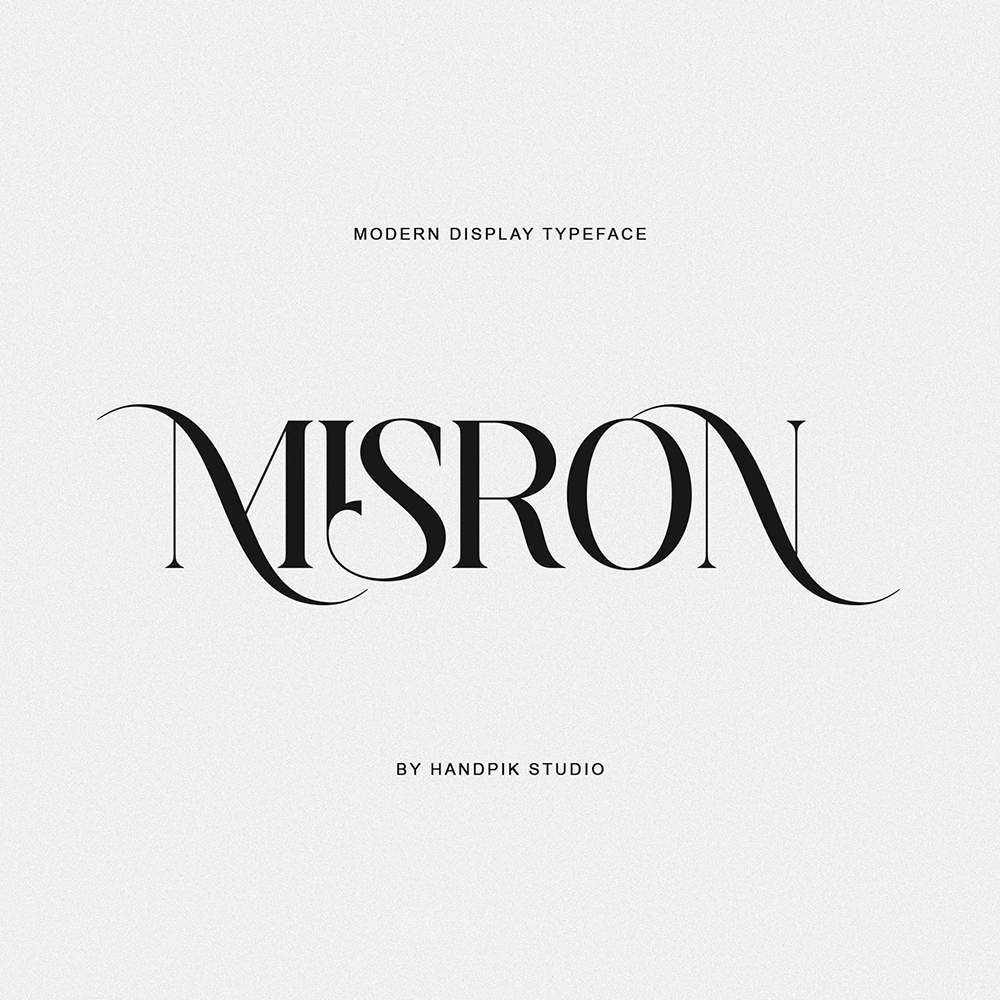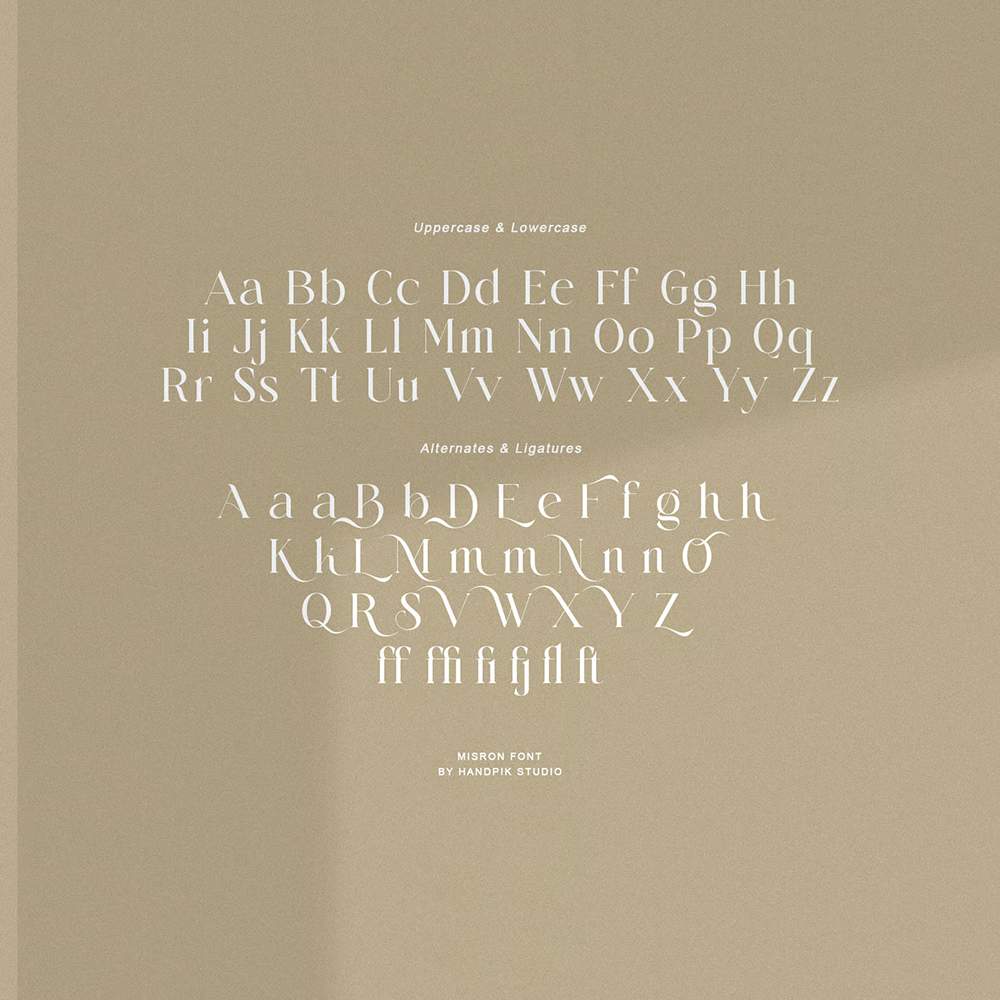
فونت پرمیوم و انگلیسی Misron Font برای بسیاری از پروژهها مانند: کتاب، مجله، لوگو، برندسازی، عکاسی، نقل قولها، هدر وبلاگ، پوستر، تبلیغات و غیره عالی خواهد بود.…
فونت پرمیوم و انگلیسی Misron Font برای بسیاری از پروژهها مانند: کتاب، مجله، لوگو، برندسازی، عکاسی، نقل قولها، هدر وبلاگ، پوستر، تبلیغات و غیره عالی خواهد بود.
مزایای استفاده از فونت لاتین Misron چیست؟